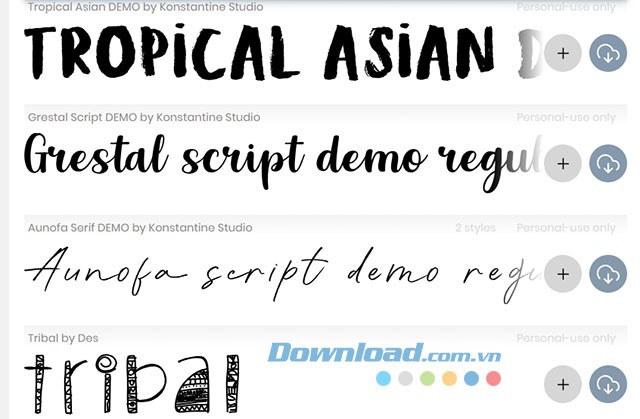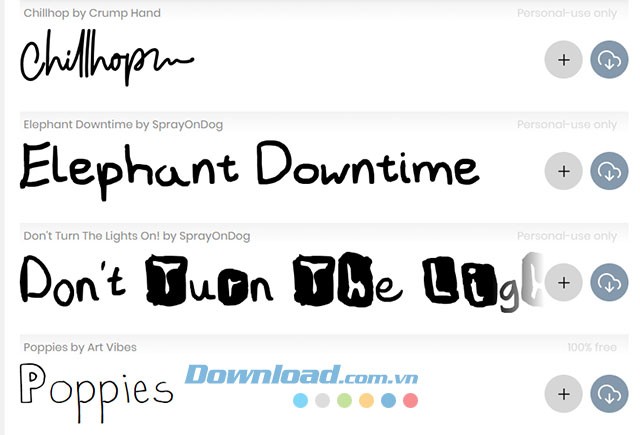
Font Chill là một bộ font chữ đẹp tiếng Anh, sở hữu rất nhiều kiểu chữ độc đáo và ấn tượng. Bộ font này hứa hẹn sẽ mang đến nguồn cảm hứng mới mẻ, tràn đầy năng lượng và niềm vui cho công việc của bạn.
Vì mang ý nghĩa tích cực, bộ Font Chill chắc chắn sẽ là nguồn cảm hứng sáng tạo tuyệt vời, đặc biệt đối với các bạn trẻ.
Bộ Font Chill bao gồm tổng cộng 21 font chữ đẹp dành cho Word , mang phong cách “Chill” đặc trưng. Đây không phải là những font chữ cứng nhắc như Font Vni , Bộ font TCVN3 hay Bộ font Unicode .
Thay vào đó, bạn sẽ có những lựa chọn mới mẻ, mềm mại và độc đáo, đảm bảo sẽ làm hài lòng mọi người. Bạn hoàn toàn có thể sử dụng Bộ Font Chill trong Photoshop để thiết kế poster một cách chuyên nghiệp.
Với những người làm trong lĩnh vực thiết kế đồ họa và chỉnh sửa ảnh, bộ Font Chill sẽ là nguồn năng lượng mới, kích thích sự sáng tạo và thử nghiệm để tạo ra những sản phẩm độc đáo, nổi bật và mang đậm dấu ấn cá nhân.